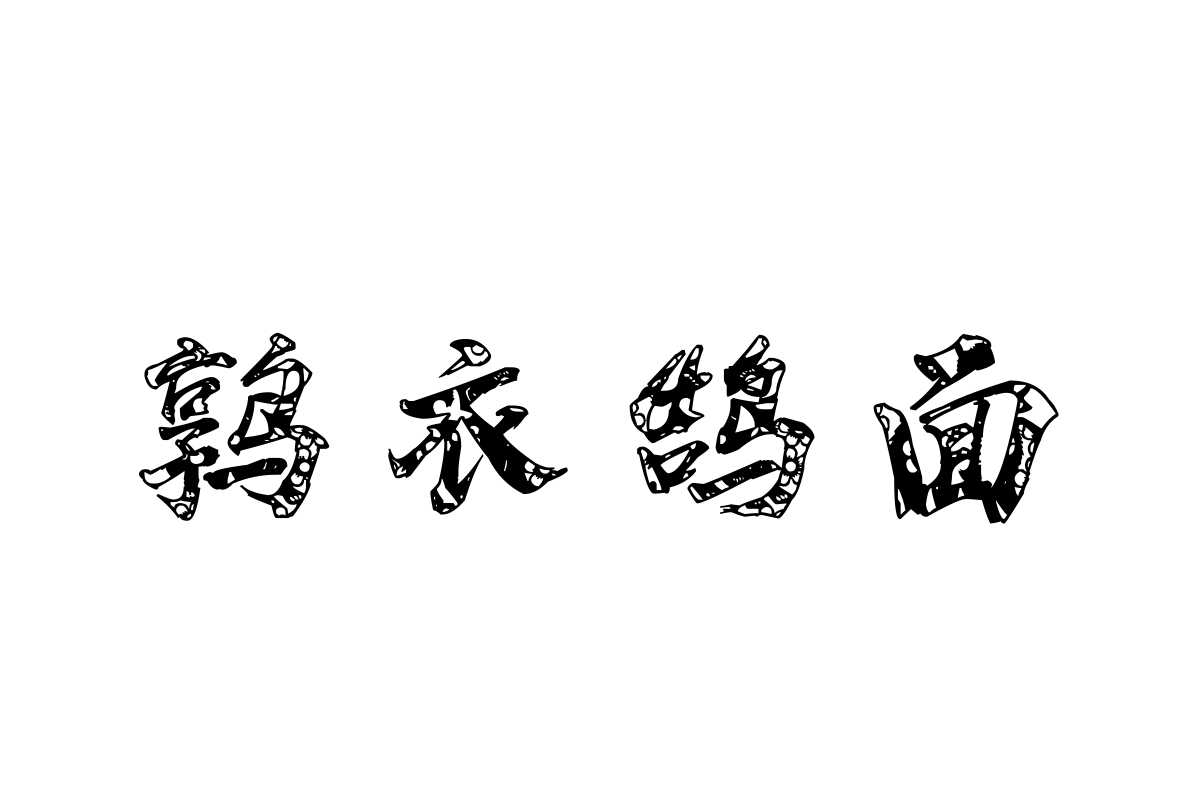
汉标年窗花字体是一种特殊的中文书法字体,它的特点是笔画流畅、结构紧凑、富有韵律感。这种字体通常用于装饰性的文字设计,如节日贺卡、海报、广告等。
汉标年窗花字体的特点如下:
1. 笔画流畅:汉标年窗花字体的笔画线条流畅自然,给人一种优雅的感觉。
2. 结构紧凑:这种字体的结构紧凑,每个字的笔画都紧密相连,使得整个字体看起来非常整齐。
3. 富有韵律感:汉标年窗花字体的笔画和结构都有一定的规律性,使得整个字体看起来富有节奏感和动感。
4. 适合装饰性文字设计:由于汉标年窗花字体的特点,它非常适合用于装饰性的文字设计,如节日贺卡、海报、广告等。
5. 易于识别:汉标年窗花字体的笔画简单明了,易于识别和记忆。
总之,汉标年窗花字体是一种具有独特韵味和艺术感的中文书法字体,适合用于各种需要装饰性文字设计的场合。